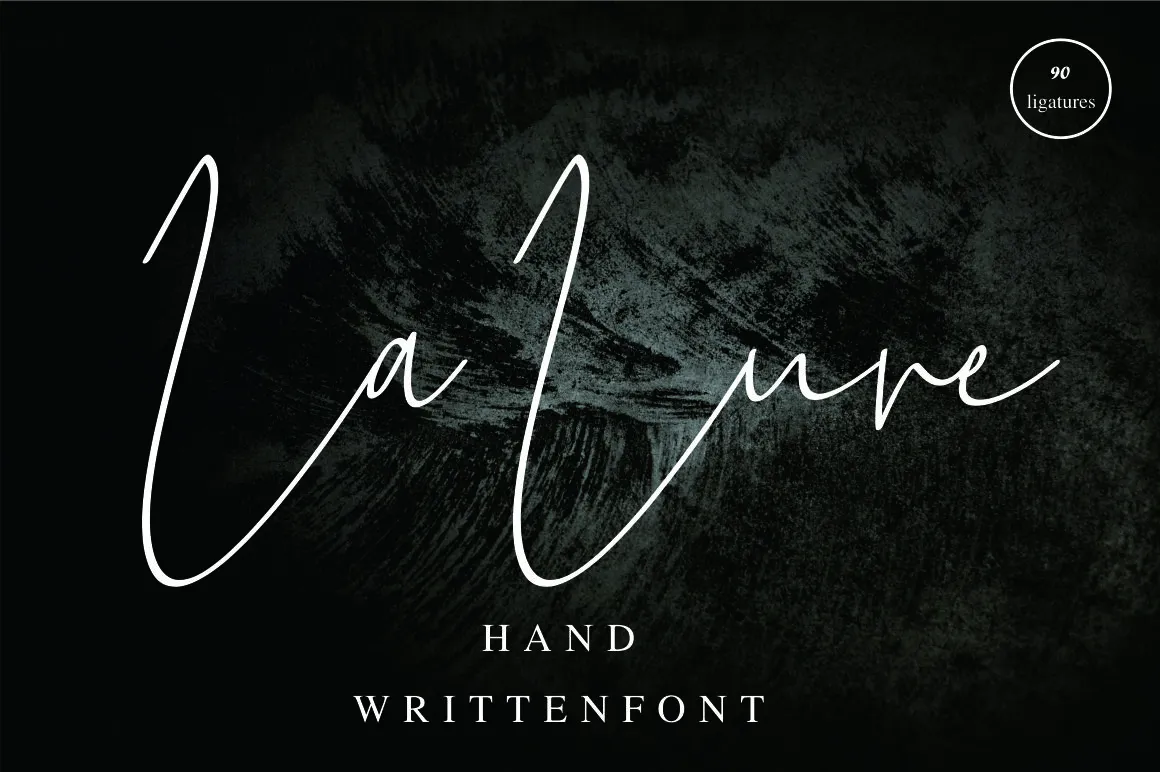
La Lune Handwritten Font – Download Grátis
Esta é uma nova assinatura-font com estilo de escrever a mão pura. Introduzimos La Lune Font. La Lune é uma font que é muito interessante para você e muito simples, então essa font será sua escolha perfeita para seus projetos como logomarca, design, revista, produto, embalagem, citações, etc. La Lune tem um charme singular que o torna um recurso indispensável para designers em busca de uma fonte elegante e versátil. Ideal tanto para trabalhos profissionais quanto para criações artísticas criativas.